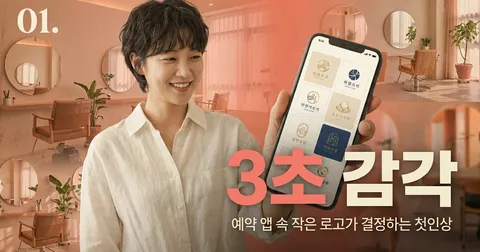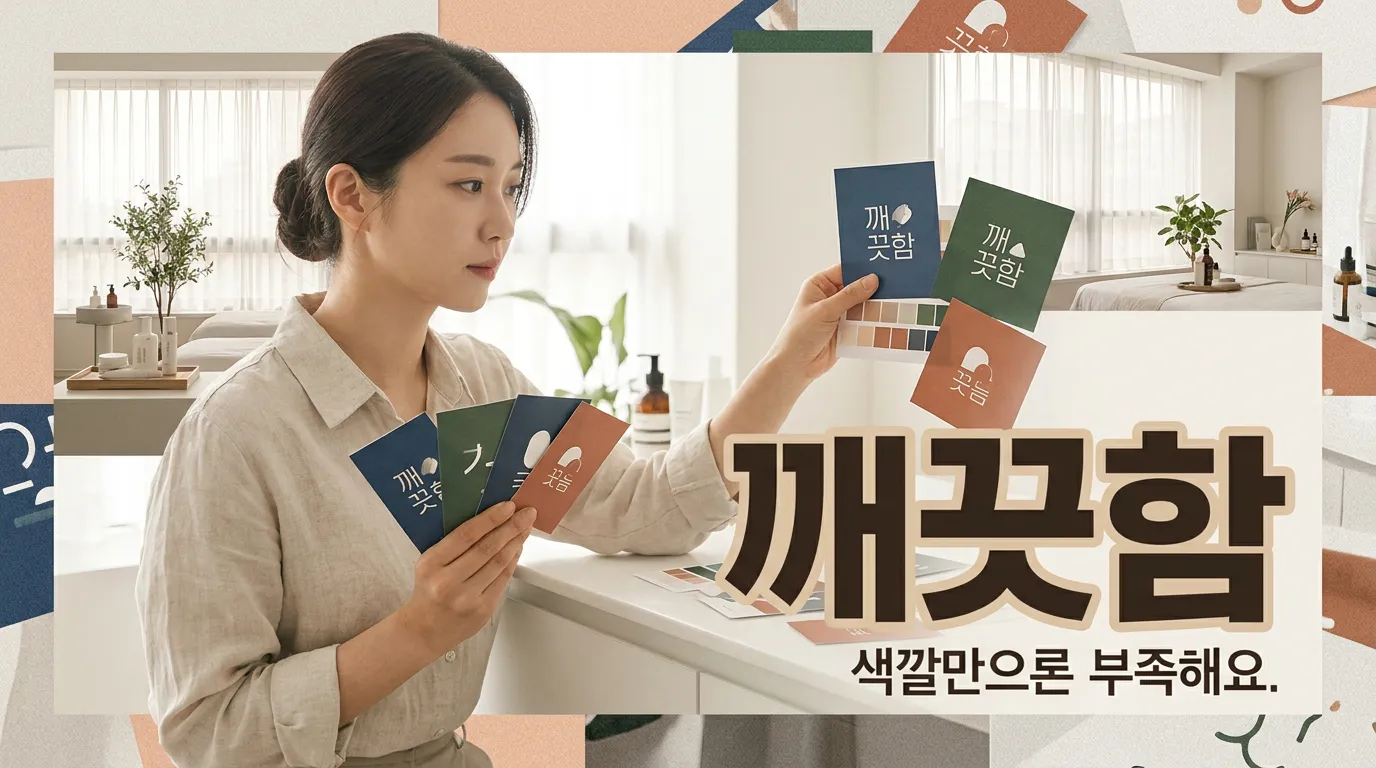
피부샵 로고, 깨끗해 보이는 색·폰트 조합 7가지
청결함과 전문성을 동시에 보여주는 피부관리샵 로고 색상, 폰트, 명도 대비 기준을 실무 관점에서 정리했습니다.
흰색 로고가 깨끗해 보일 줄 알았는데, 막상 붙여보니 병원도 카페도 아닌 애매한 느낌이 날 때가 있습니다.
왜 흰색만 쓰면 오히려 비어 보일까요?
원장님들이 가장 많이 고르는 색은 화이트, 아이보리, 베이지입니다. 틀린 선택은 아닙니다. 문제는 ‘흰색’이 아니라 흰색 옆에 무엇을 붙이느냐입니다.
피부관리샵은 미용업이지만, 손이 얼굴에 닿고 기기와 소모품이 보이는 업종입니다. 공중위생관리법에서도 미용업은 위생관리 기준을 따로 둡니다. 고객은 예쁜지보다 먼저 “여기 깨끗한가?”를 봅니다. 그래서 로고도 장식보다 정리된 인상이 먼저 와야 합니다.
먼저 이렇게 잡으세요. 1) 화이트 + 메디컬 블루 + 정직한 고딕. 피부 문제 개선, 여드름, 재생 케어 쪽에 맞습니다. 2) 아이보리 + 세이지 그린 + 부드러운 고딕. 예민 피부, 진정 관리, 자연 유래 콘셉트에 좋습니다. 단, 초록을 진하게 쓰면 한의원처럼 보일 수 있어 채도를 낮춰야 합니다.
전문샵처럼 보이려면 어떤 색을 피해야 할까요?
깨끗함을 망치는 건 색 자체보다 ‘달콤한 색의 과다 사용’입니다. 연핑크, 살구, 로즈골드를 크게 쓰면 피부관리보다 속눈썹·네일·디저트 쪽으로 기울어집니다.
저라면 중심 색은 차갑게, 보조 색은 따뜻하게 둡니다. 3) 펄 그레이 + 딥 네이비 + 얇지 않은 고딕. 고가 관리, 리프팅, 안티에이징에 어울립니다. 4) 페일 민트 + 차콜 + 둥글지 않은 산세리프. 위생감은 살리고 병원 느낌은 덜어냅니다. 5) 웜 베이지 + 뮤트 로즈 + 세리프 한 글자 포인트. 1인샵의 온도는 남기되, 로고 전체를 핑크로 밀지 않는 방식입니다.
최근 색채 관련 의료·복식 연구에서도 흰색은 깨끗하고 청결한 느낌과 연결되어 다뤄집니다. 저는 여기서 핵심을 하나만 봅니다. 흰색은 혼자 일하지 않습니다. 옆의 회색, 남색, 초록이 방향을 정합니다.
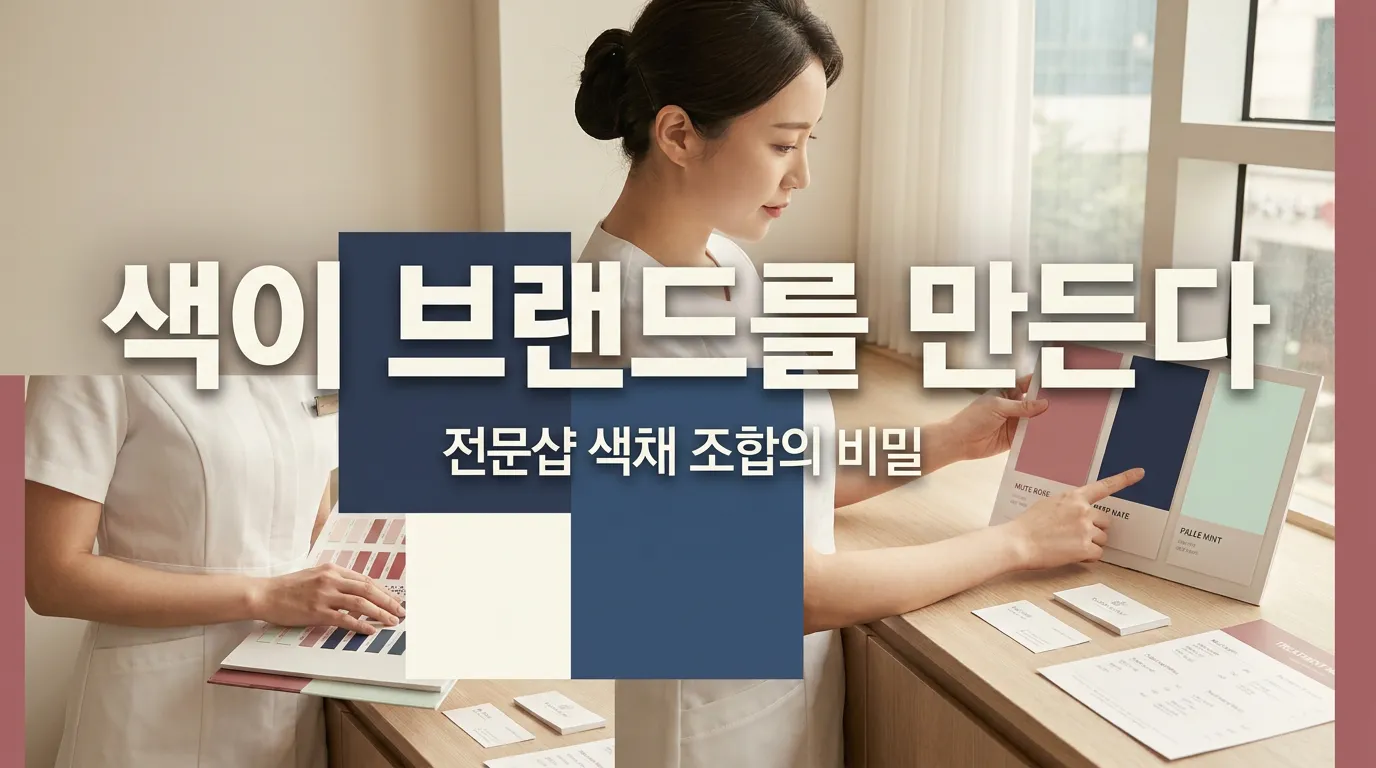
폰트는 예쁘면 되는 걸까요?
아닙니다. 작은 예약 앱 아이콘에서 뭉개지는 폰트는 매장 유리문에서 예뻐도 실패입니다. 피부관리샵 로고 디자인은 인스타 프로필, 네이버 플레이스, 가격표, 제품 라벨까지 같이 봐야 합니다.
그래서 6) 라이트 아쿠아 + 다크 틸 + 중간 굵기 고딕을 추천합니다. 물광, 수분, 진정 이미지를 주면서도 글자가 선명합니다. 7) 화이트 + 실버 그레이 + 블랙 한 줄 + 고급 세리프도 가능합니다. 다만 실버는 인쇄와 간판에서 흐려지기 쉬워, 로고 원본에는 반드시 진한 보조 버전을 같이 만들어야 합니다.
웹 접근성 기준에서는 일반 텍스트와 배경의 명도 대비를 4.5:1 이상으로 봅니다. 로고가 법적으로 전부 이 기준을 따라야 한다는 뜻은 아닙니다. 다만 작은 화면에서 읽히는지 확인하는 최소한의 실무 기준으로 쓰기 좋습니다.
지금 시안에서 무엇부터 고치면 될까요?
색을 더 넣기 전에 빼야 합니다. 로고 안에 물방울, 잎, 얼굴선, 손, 별빛이 다 들어가 있으면 고객은 한 번에 아무것도 기억하지 못합니다.
제가 현장에서 보면 오래 가는 피부관리샵 로고는 대체로 조용합니다. 색은 2개, 폰트는 1개, 심볼은 하나의 움직임만 남깁니다. 청결함은 밝은 색에서 오고, 전문성은 절제에서 옵니다.